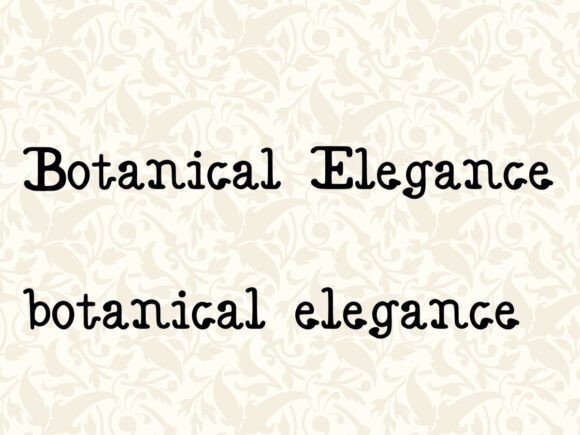
Botanical Elegance
適切なデザイン要素を見つけるのは難しい場合がありますが、Botanical Eleganceは作品を即座に引き立てる優れたコレクションを提供します。
POD(オンデマンド印刷)製品、結婚式の招待状、またはソーシャルメディアのグラフィックを作成している場合でも、Botanical Eleganceは理想的です。